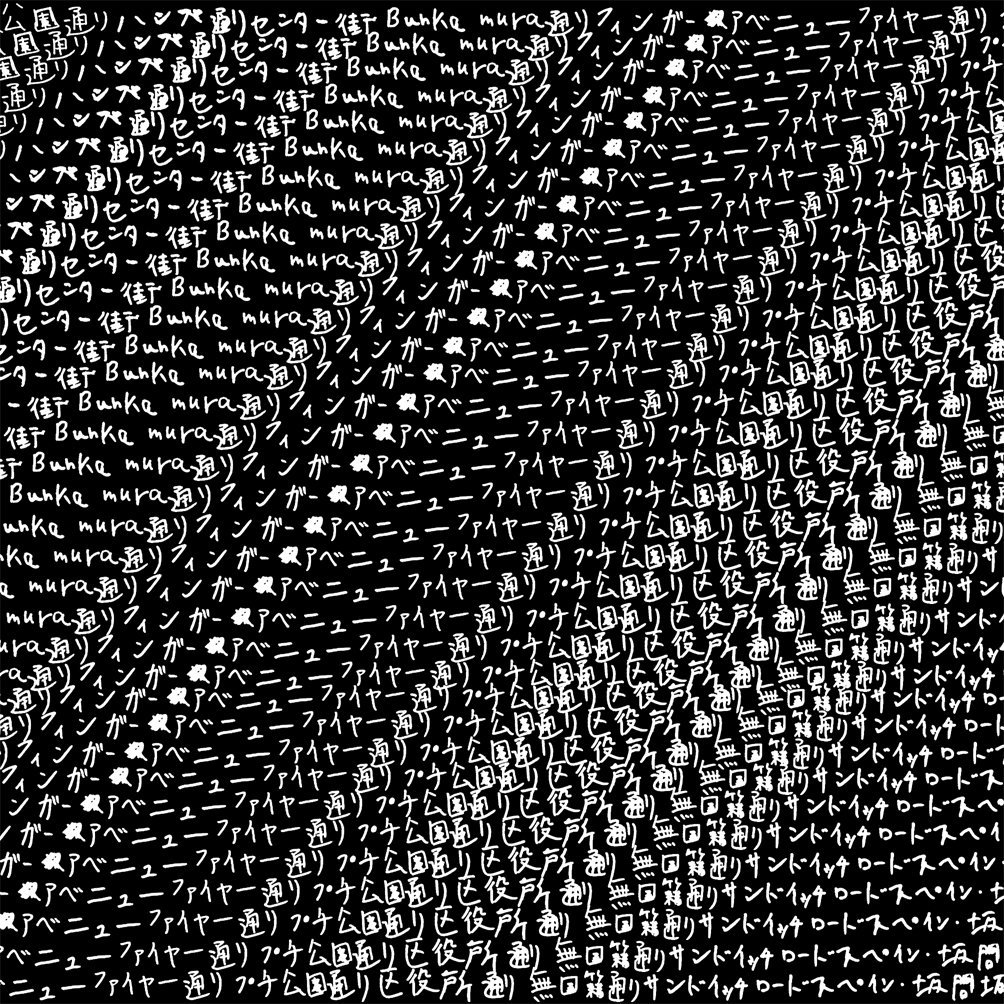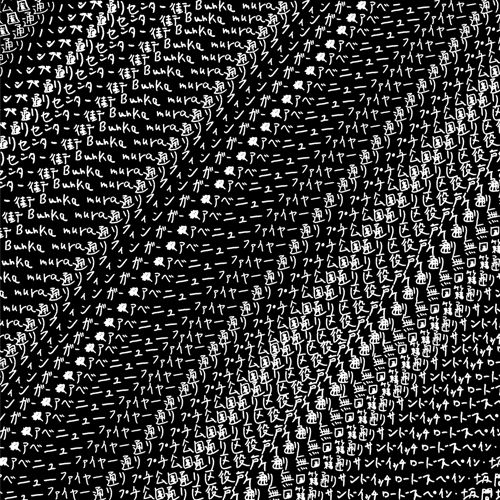
ストリートストライプ 1
ArtistQtto
Designer西塚 音緒
Organization渋谷アトリエ福花
アトリエ福花のメンバーが、シブヤをイメージしてイラストを直観で描いたり、粘土でじっくりアルファベットを作ったりしました。ブランドネーム[Qtto]の通り、シブヤの街をキュッとまとめたユニークな仕上がりになりました。遊び心で色々楽しんでください。(渋谷アトリエ福花)